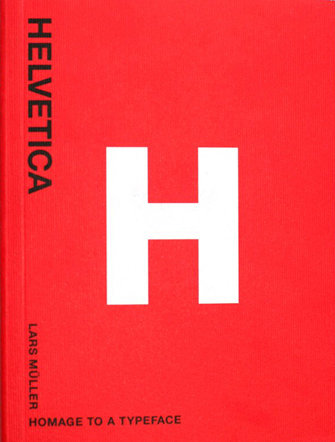
1957 entwarf der Schweizer Schriftgestalter Max Miedinger die «Neue Haas Grotesk», die nach 1960 als »Helvetica« zum weltweit meistverwendeten Schrifttyp werden sollte. Die Helvetica verkörperte das Ideal der Sachlichkeit, das damals von der Schweizer Grafik propagiert wurde.
Dieses Buch ist eine Hommage an die Helvetica, den Schichtarbeiter unter den Schrifttypen, an ihren vergessenen Gestalter Max Miedinger und all diejenigen, welche während der letzten 40 Jahre zu ihrem unvergleichlichen internationalen Triumphzug beigetragen haben. Die gestalterischen Arbeiten, hier zu Ehren der Helvetica zusammengetragen, wurden von hervorragenden Designern und anonymen Amateuren aus der ganzen Welt kreiert. Sie präsentieren eine glanzvolle Sammlung dieser Ikone des modernen Designs. Helvetica ist nicht nur die bevorzugte Schrift von führenden Profis, sie ist auch die Favoritin bei der anonymen Gestaltung der Zeichen und Signale, Hinweise und Verbote, die das städtische Leben regeln.
Helvetica
Homage to a Typeface
Design: Integral Lars Müller